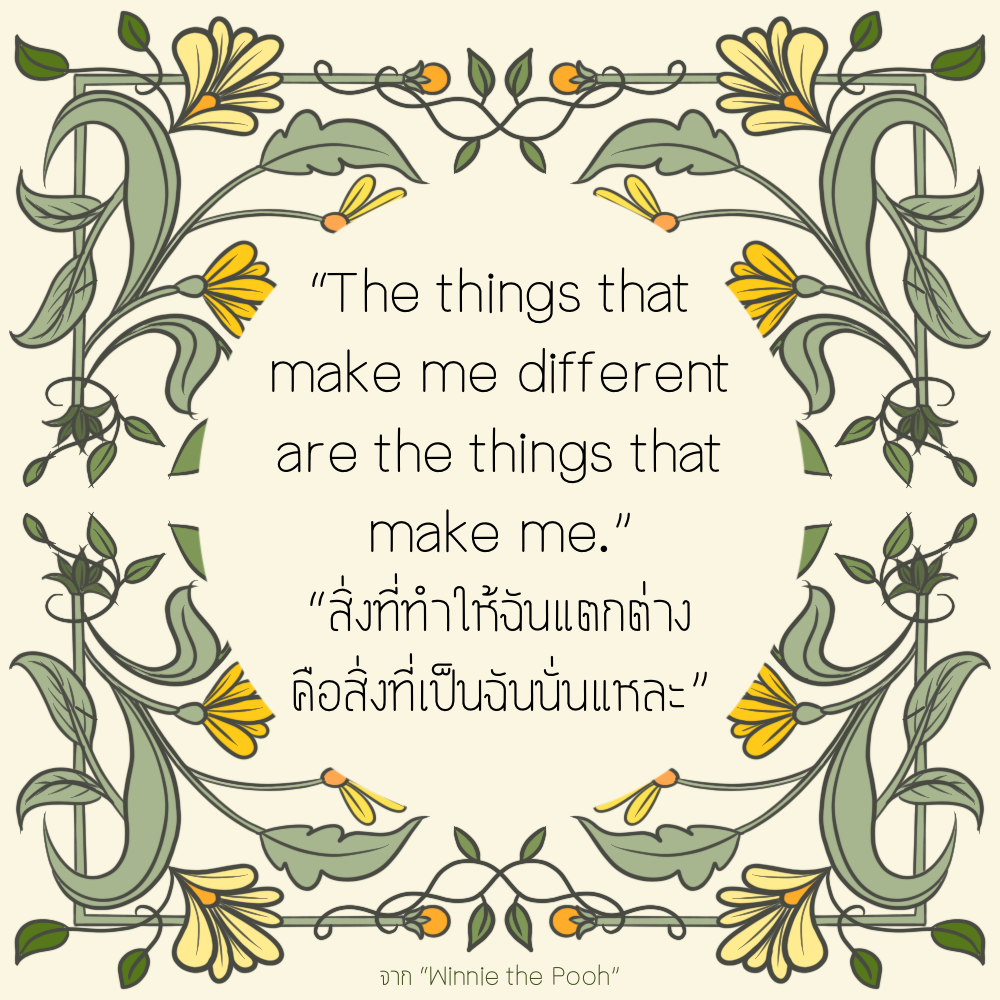
ทอศิลป์ ใจดีมาก
พัฒนาฟอนต์นี้ต่อมาจากฟอนต์ "ทอศิลป์ ภาณุพันธุ์" และเปลี่ยนตัวภาษาอังกฤษใหม่หมด
เป็นฟอนต์ลักษณะตัวดิสเพลย์ที่บาง สามารถใช้เป็นฟอนต์พื้นได้ด้วย
ฟอนต์ "ทอศิลป์ ใจดีมาก"